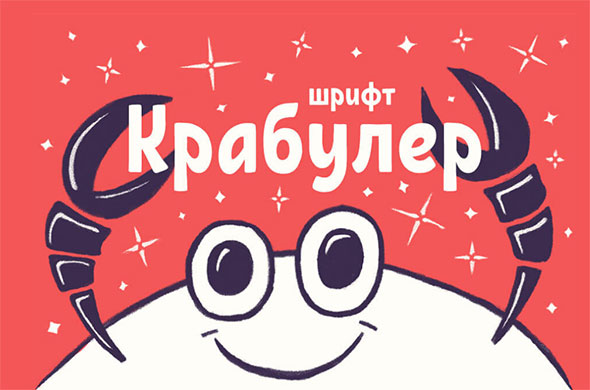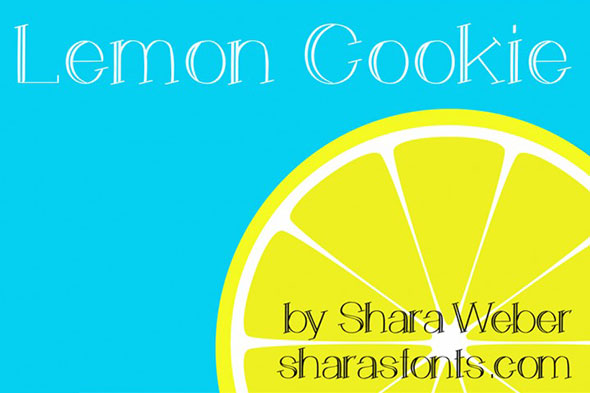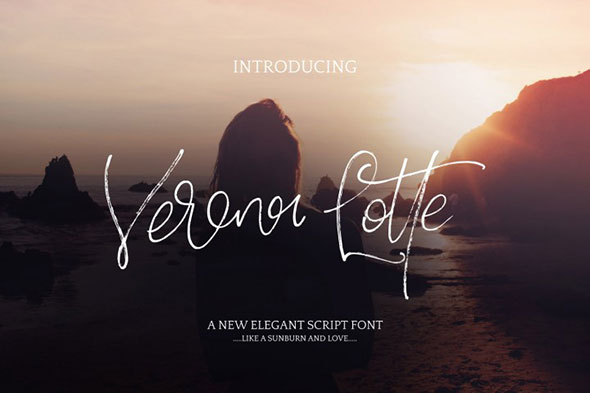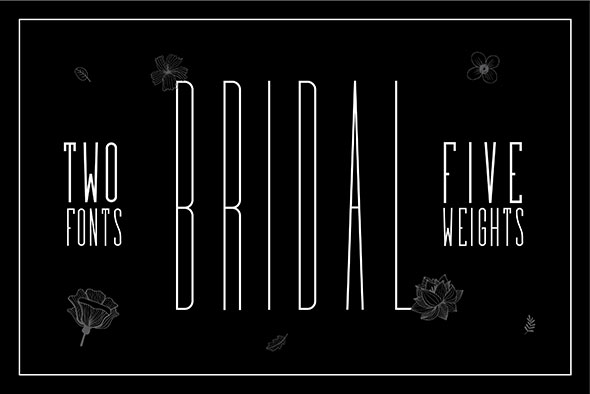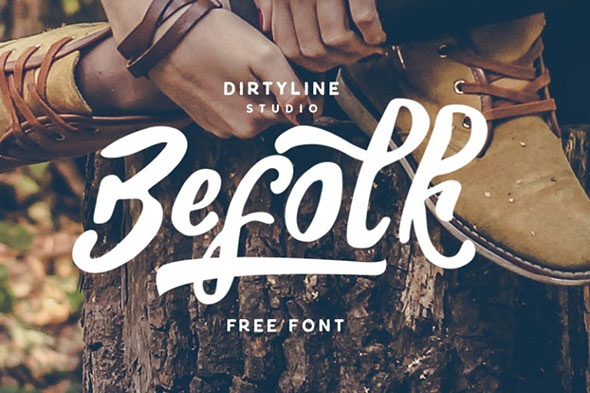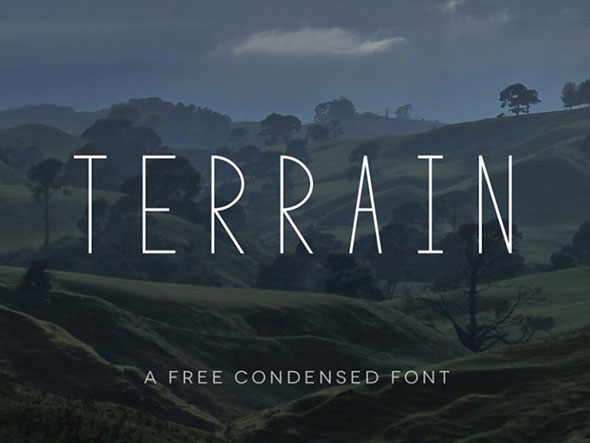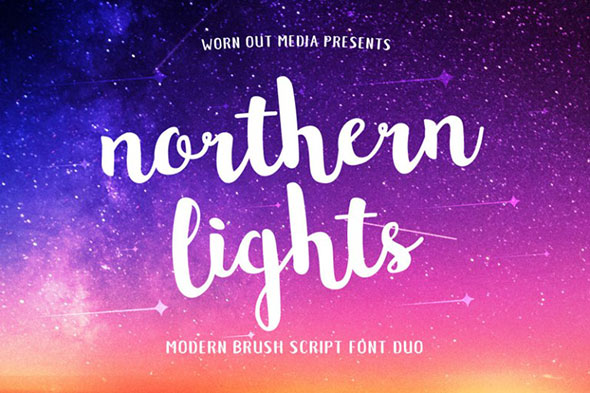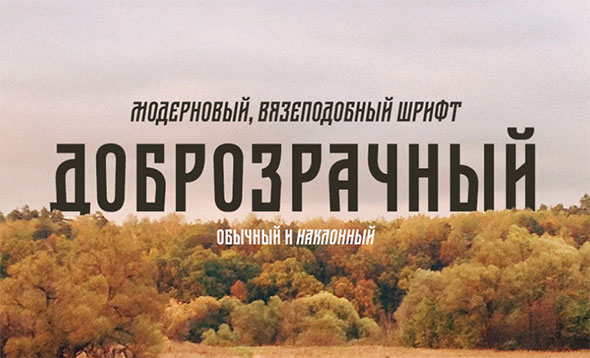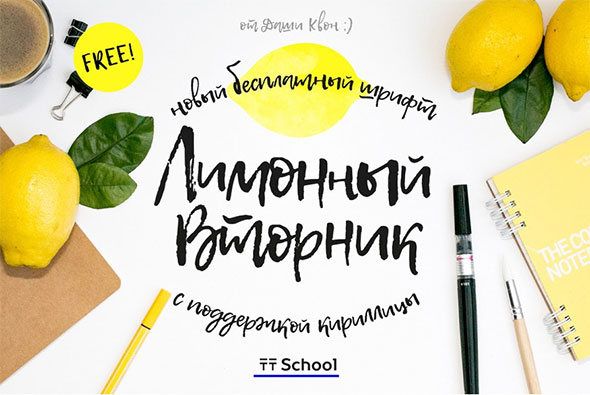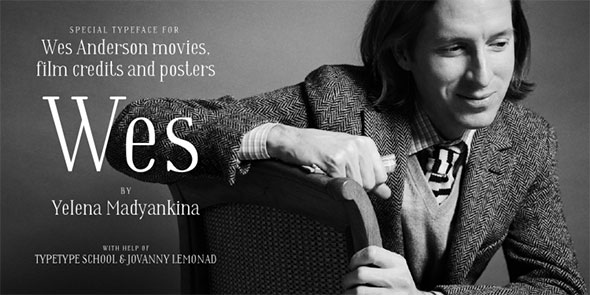
15 бесплатных шрифтов для вашего дизайна
Пополняем коллекцию бесплатных шрифтов. Мы собрали 15 гарнитур, которые пригодятся вам в оформлении проектов. Вы найдете вполне практичные варианты, а также декоративные начертания для особых случаев. В первой части подборки шрифты с кириллическим вариантом, а во второй – только латиница.
Кириллица
Крабулер
Доброзначный
DEUX
Magnolia
Lemon Tuesday
Wes
Opinion Pro
MADE Likes
Латиница
Curely
Lemon Cookie
Verona Lotte
Bridal
Befolk
Terrain
Northern Lights